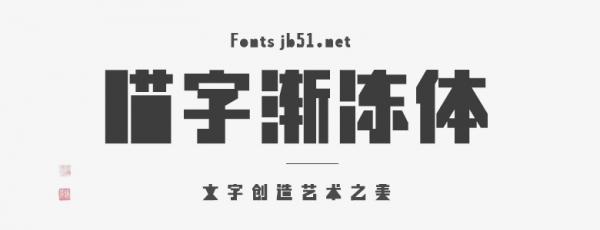
喵字渐冻体
喵字渐冻体是一款具有深远意义的定制级字库产品,其设计初衷是为了让大众更加直观地了解渐冻症患者的痛苦与挣扎。渐冻症,又称肌萎缩侧索硬化(ALS),是一种罕见但严重的神经系统疾病,患者会逐渐丧失运动能力,直至无法动弹。设计团队希望通过喵字渐冻体这一创新方式,模拟渐冻症的病理特征,引起社会的广泛关注,从而推动医学技术的进步,为患者带来希望。